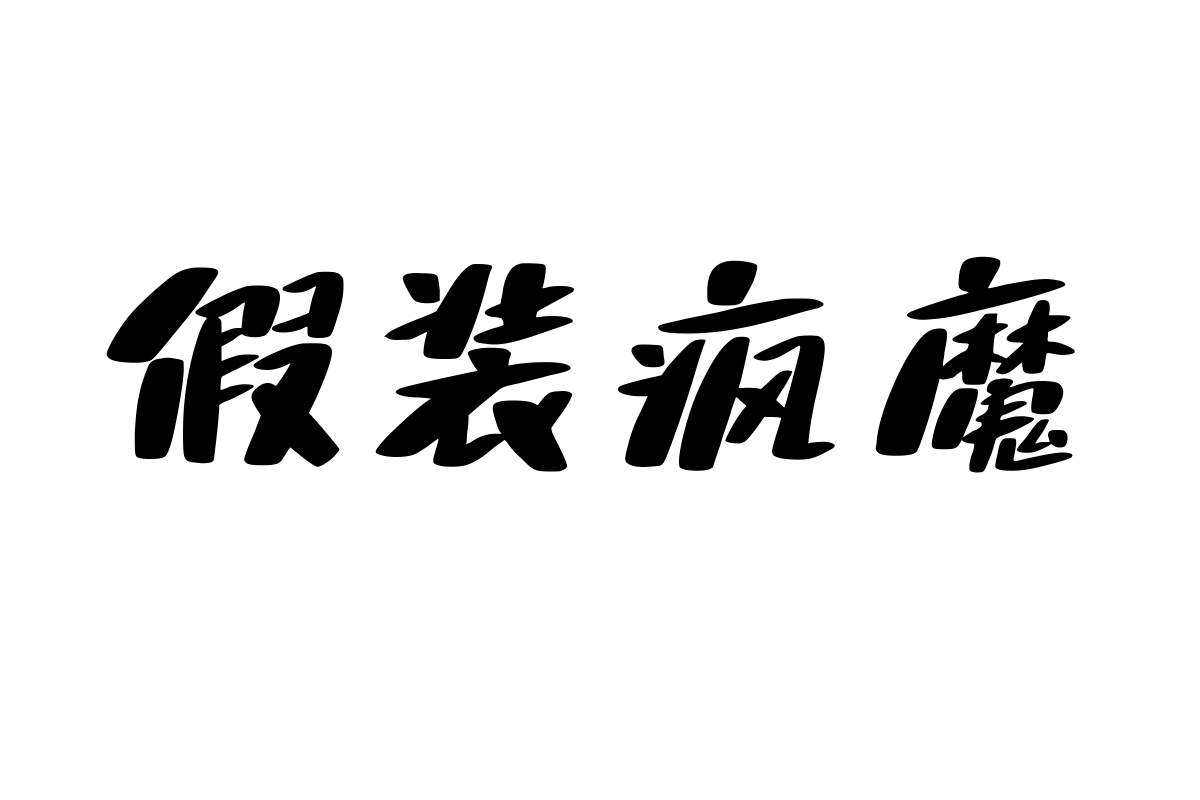
三极倾城体,又称“三极字体”,是一种由中国设计师王家宏于2005年设计发布的中文字体。这种字体以其独特的字形结构和现代感而受到广泛欢迎。
三极倾城体的特点如下:
1. 字形结构:三极倾城体的字形结构独特,笔画粗细不一,呈现出一种动态的美感。这种结构使得文字在视觉上更具吸引力和表现力。
2. 字体风格:三极倾城体具有现代感和时尚感,适合用于广告、包装、杂志等需要突出视觉效果的场合。同时,由于其独特的字形结构,也适合用于一些需要强调个性和创意的设计作品。
3. 应用场景:三极倾城体适用于各种中文排版场景,如报纸、杂志、广告、网站等。它不仅适合印刷媒体,也适合数字媒体和移动设备上的展示。
总之,三极倾城体是一款极具个性和创新性的中文字体,适合用于需要突出视觉效果和个性表达的各种设计场景。